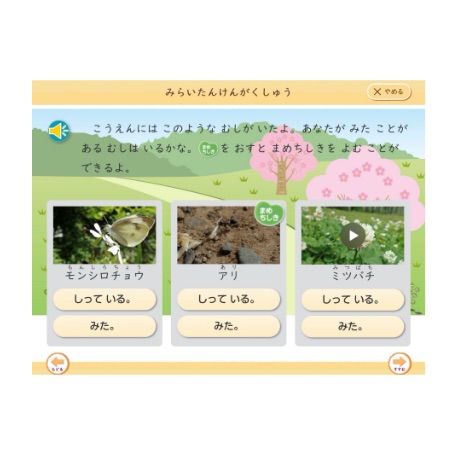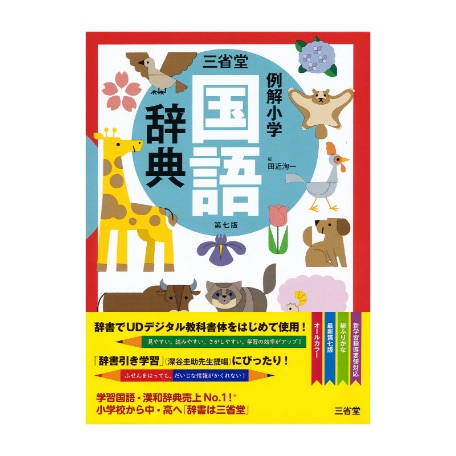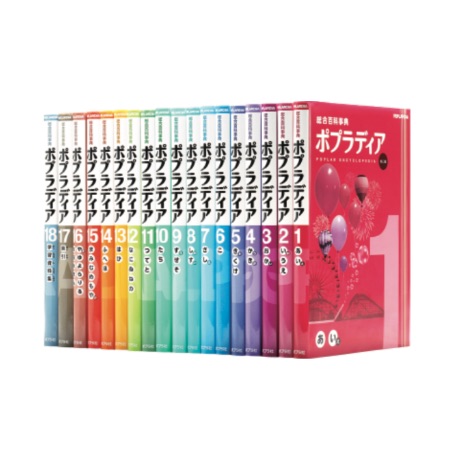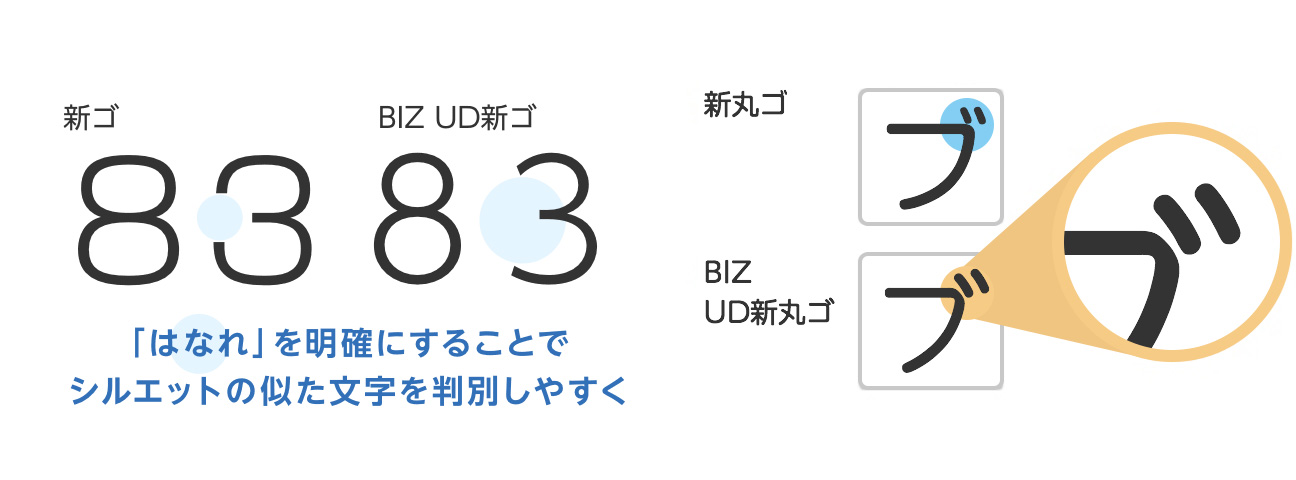
使用書体:UDデジタル教科書体
年齢や障害の有無、個々の能力差などにかかわらず、多くの人々が利用しやすいように「ユニバーサルデザイン」の思想が文字に込められた「モリサワのUDフォント」。教育委員会、学校、自治体などが、ユニバーサルデザインの実現の手段として採用しています。
初めてアルファベットを勉強する子どもたちにとって最適な、見たとおり真似して書くことができるUDデジタル教科書体の書き学習用欧文、そのポイントをご紹介しています。
教育現場では多様な子どもたちがともに学んでいます。文科省が実施した調査結果では、通常学級の中で「発達障害の可能性がある」とされた児童生徒の割合は8.8%でした。特別支援学校などに通っている発達障害やロービジョン(弱視)の児童生徒を含めるとさらに割合は大きくなります。
モリサワは、教育の中で必要不可欠な「教科書体」をユニバーサルデザインに対応させた「UDデジタル教科書体」を開発しました。
2019年に大阪医科大学LDセンター奥村氏が読み書きに困難さがある小学生2~6年生33人を対象として実施した検証では、読み速度が9%改善されることがわかりました。
教育現場での採用も始まり、文字を通じたインクルーシブ教育が進んでいます。
使用書体:UDデジタル教科書体
人は情報の80%以上を視覚から得ていると言われています。
そして、その視覚情報のほとんどは、「文字」によってもたらされていることは、もはや疑いのないことでしょう。
自治体が目指す共生社会において、「文字」をUDフォントに変えることで、「伝わる情報発信」を後押しすることが可能です。
自治体から発信される情報は子ども・高齢者・障害者とわず、全てのかたの生活に欠かせない大切な情報です。「伝える」情報を「伝わる」情報へ。可読性に優れたUDフォントが、情報のユニバーサルデザイン化を後押しします。